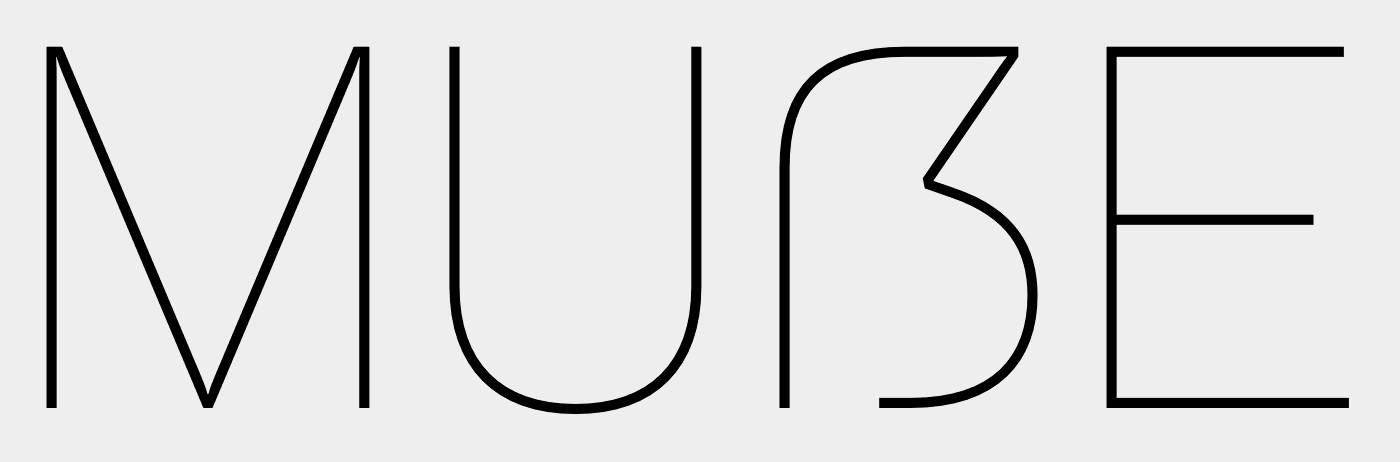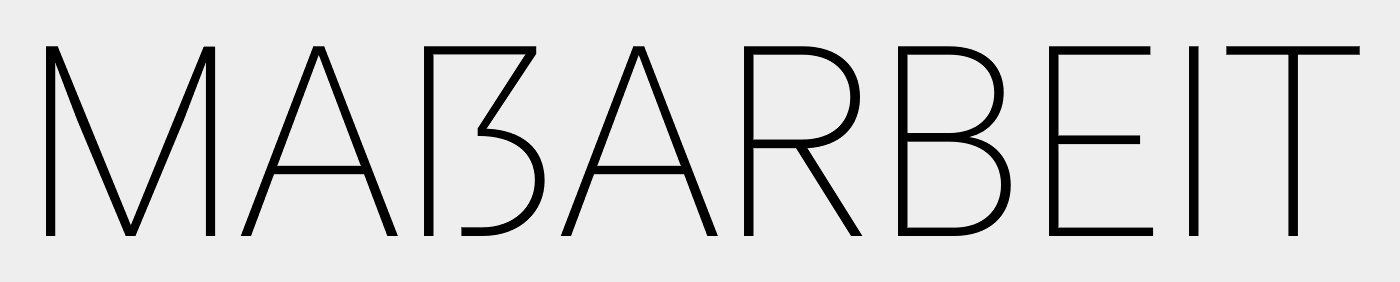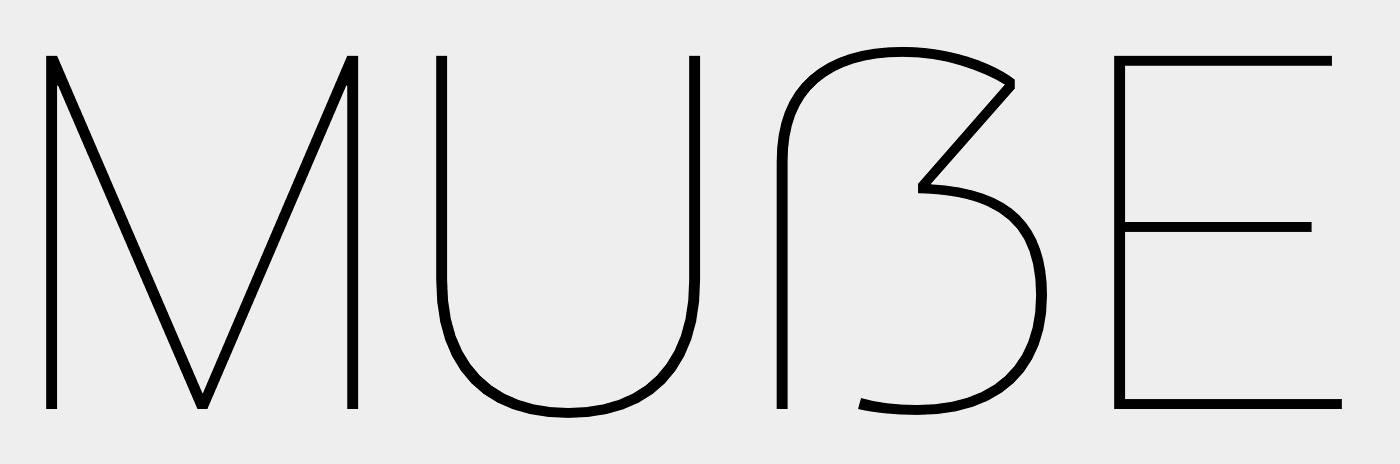
Passendes Versal-ß gesucht
Parallel könntest Du natürlich auch mal spaßenshalber bei Christian Schwartz um Support bitten. ;-)
Das kläre ich gerade mit dem Kunden.
Die Applied Sans ist mir eben noch eingefallen:
Musst halt mal schauen wie Strichstärken-konform die alle mit der Graphik sind. Das habe ich nicht getestet. Zumindest passen sie alle in die Kategorie statische Serifenlose und bieten auch ähnlich viele Schnitte.